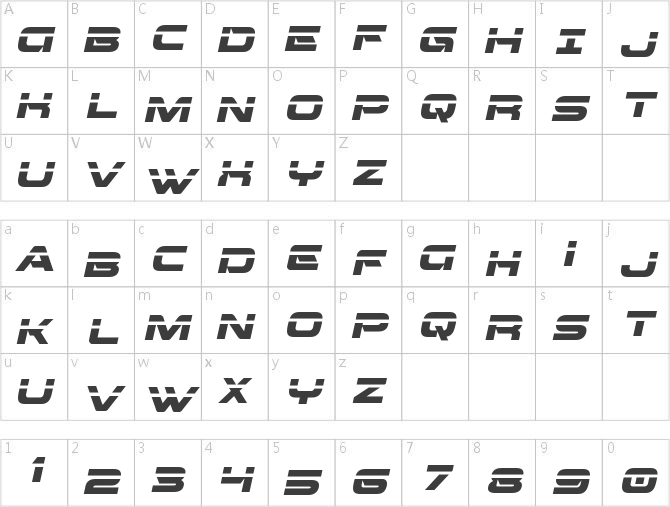
Beam Weapon Laser Italic
Beam Weapon Laser Italic介紹
Beam Weapon Laser Italic字體字庫是一款讓人賞心悅目、百看不厭的英文字體,適合各類廣告和產品包裝設計應用,字體大小0.03MB,格式為ttf字體,上傳用戶是隨緣゜,作者/版權方為未知